描き文字のデザイン
株式会社グラフィック社発行による雪朱里氏著書「描き文字のデザイン」が2017年4月10日に発売となった。
「描き文字のデザイン」は、日本を代表する明治、大正、昭和生まれのデザイナー・画家45名による「描き文字(図案文字・デザイン文字)」の仕事を800点以上の図版とともに紹介した「描き文字デザイン」本。
同書では、作家ごとにその「描き文字」仕事(装丁、ポスター、パッケージ、ロゴ、映画、テレビなど)を紹介しており、作家の生年順に掲載することで時代ごとの作風の変化を感じながらB5判による272ページのオールカラーで余すところなく描き文字の世界を体験できる。
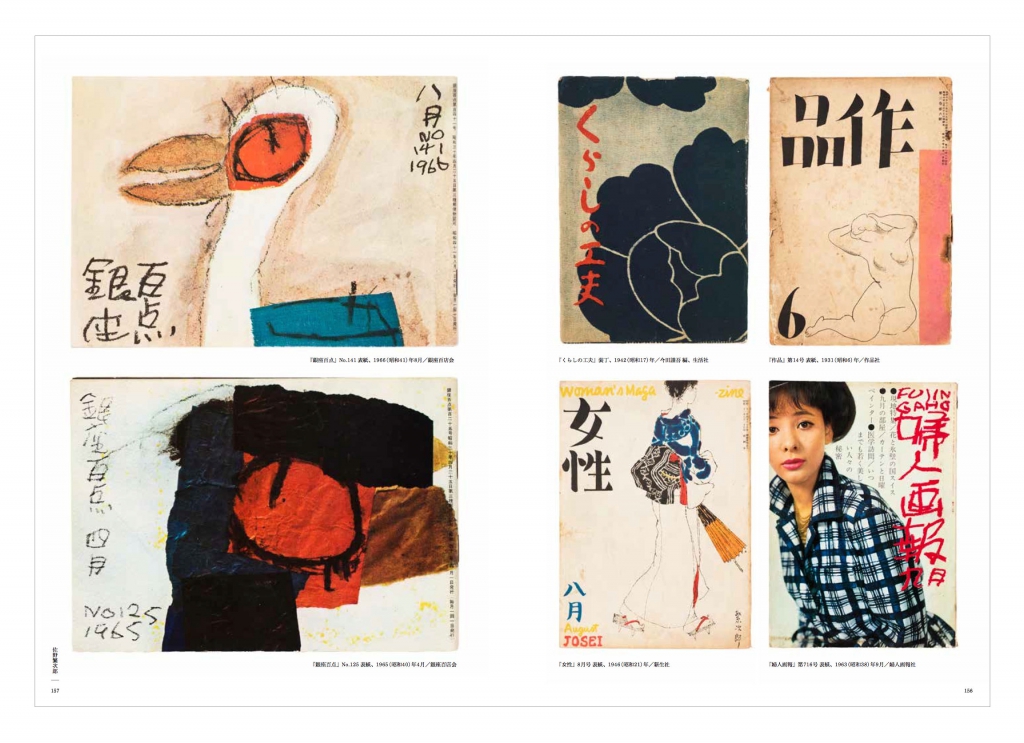
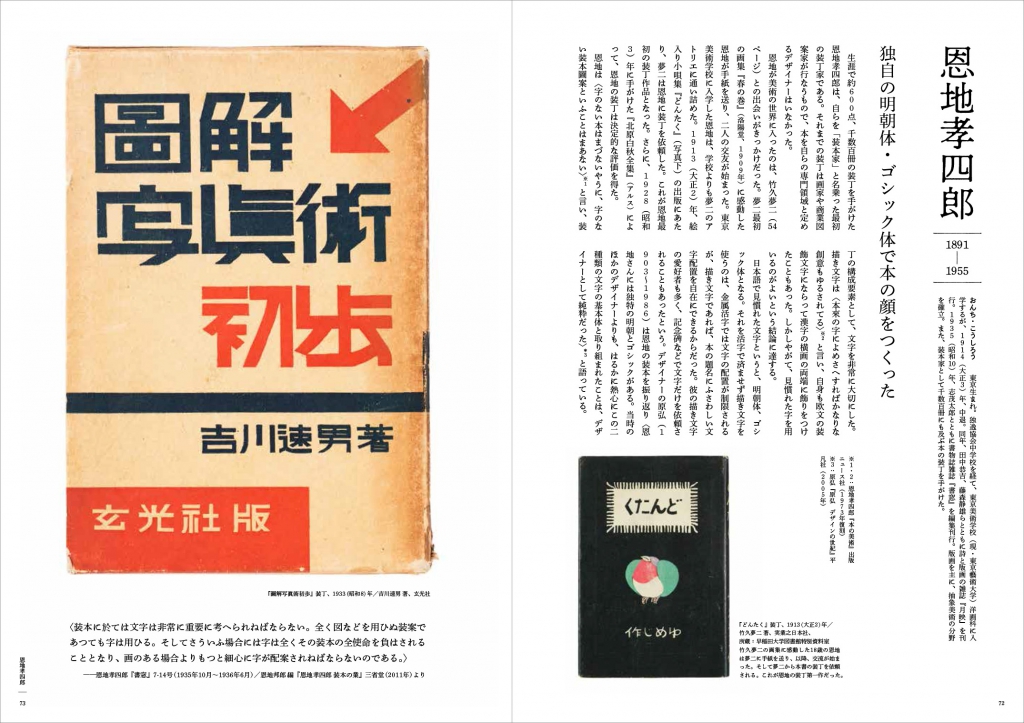
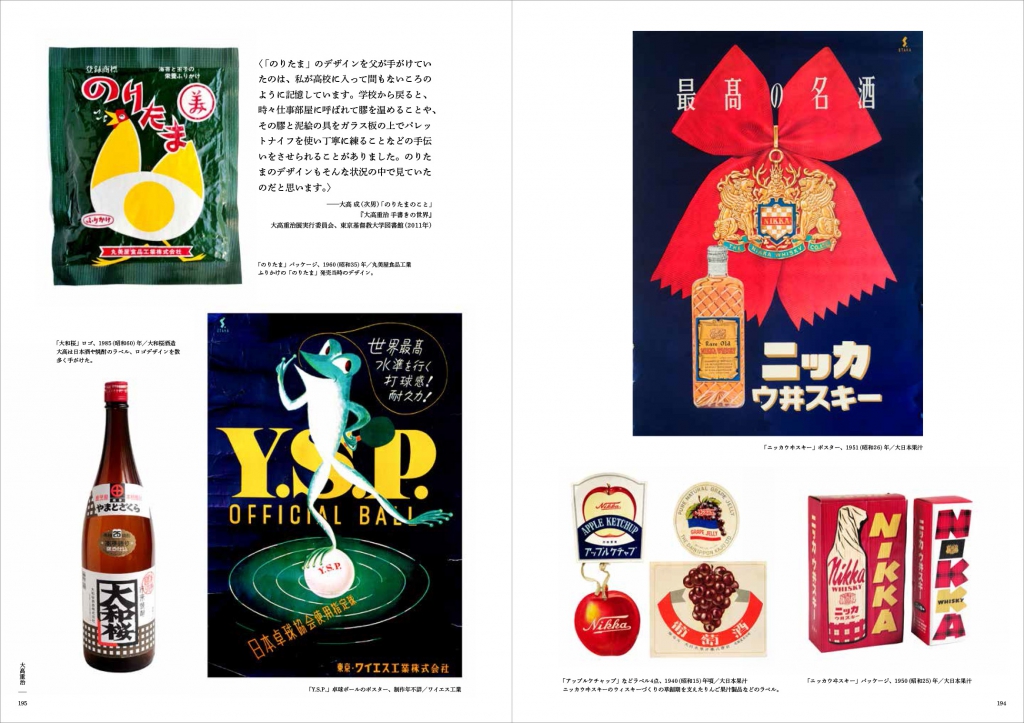
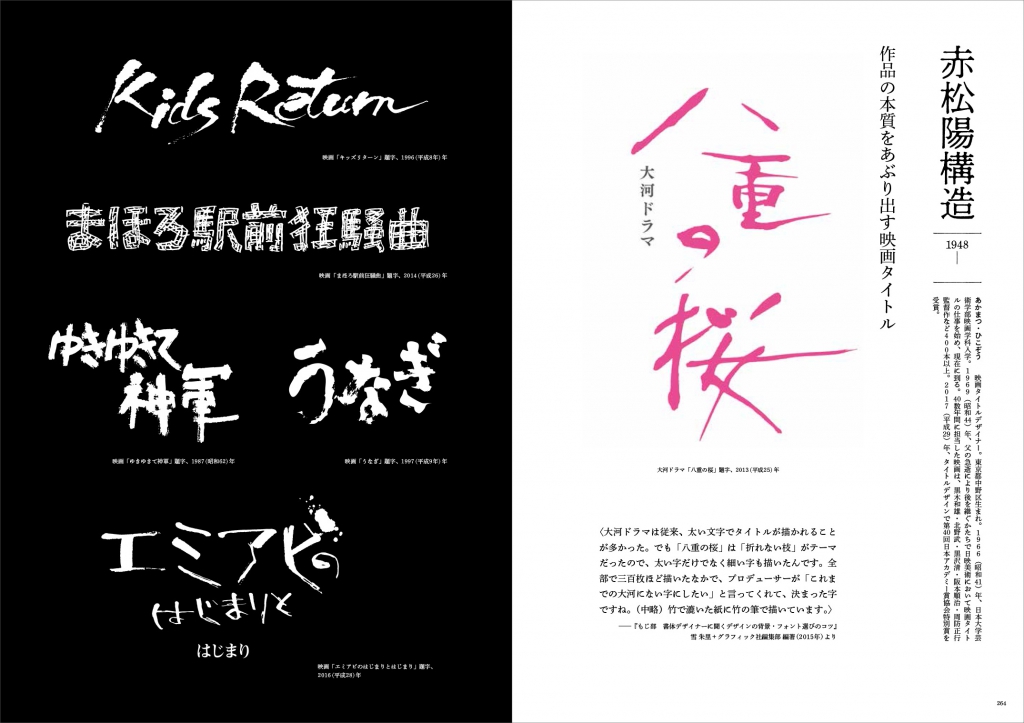
▼檜垣紀六氏に実際に描き文字を描く様子も実演。
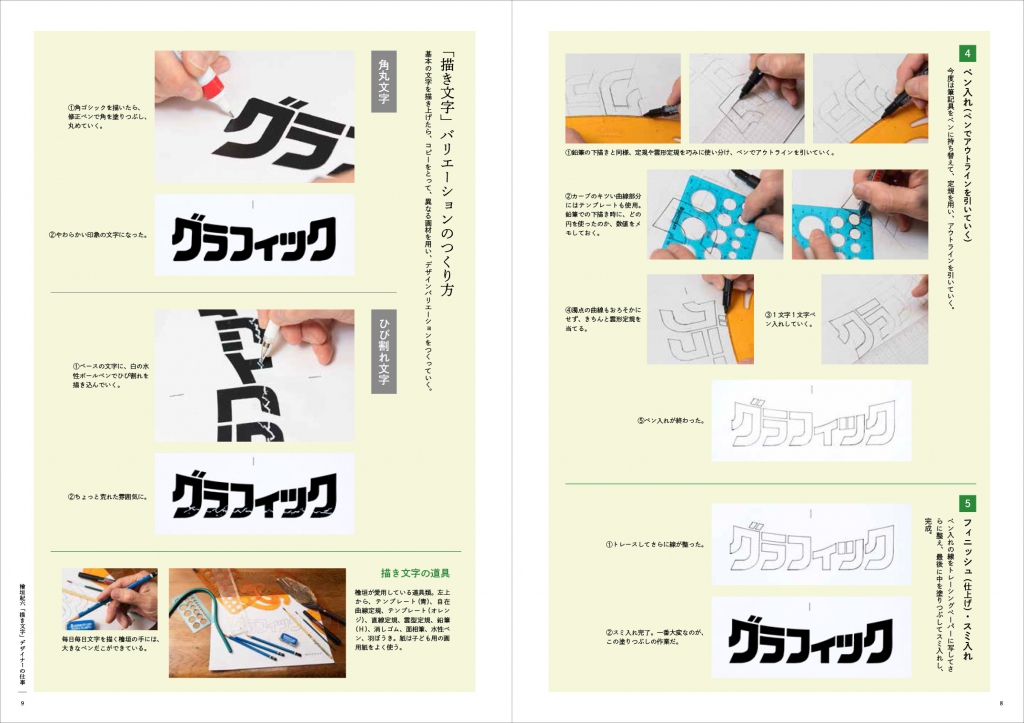
▼収録作家45名(生年順)
中村不折
藤島武二
杉浦非水
橋口五葉
竹久夢二
小出楢重
岡本帰一
広川松五郎
岸田劉生
恩地孝四郎
中川一政
武井武雄
芹沢銈介
初山滋
山六郎
吉田謙吉
田河水泡
柳瀬正夢
佐野繁次郎
村山知義
畦地梅太郎
山田伸吉
今竹七郎
早川源一
河野鷹思
奥山儀八郎
大高重治
野口久光
花森安治
高橋錦吉
中原淳一
大橋正
鳥居敬一
田村義也
堂昌一
綿貫宏介
篠原榮太
竹内志朗
宇野亞喜良
和田誠
山藤章二
平野甲賀
檜垣紀六
赤松陽構造
望月通陽